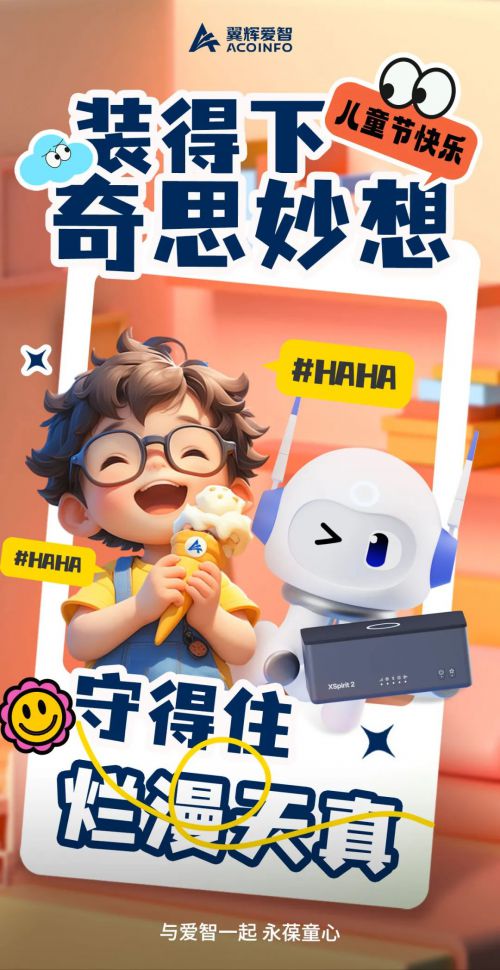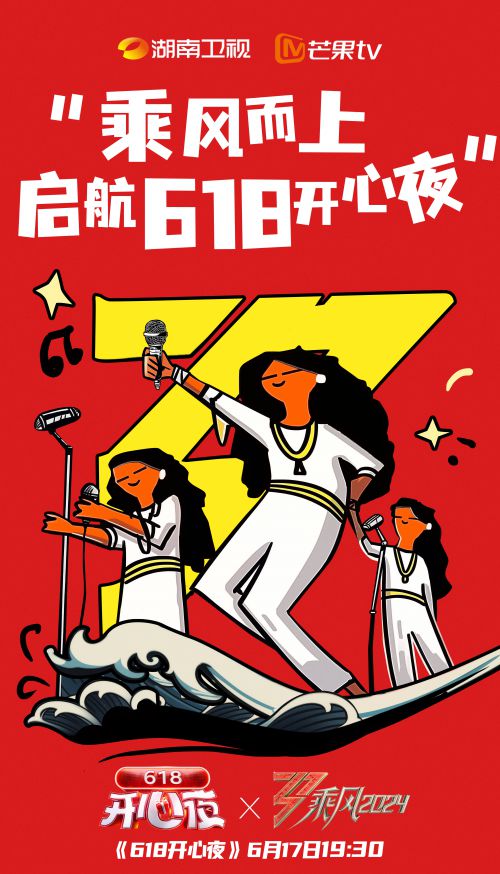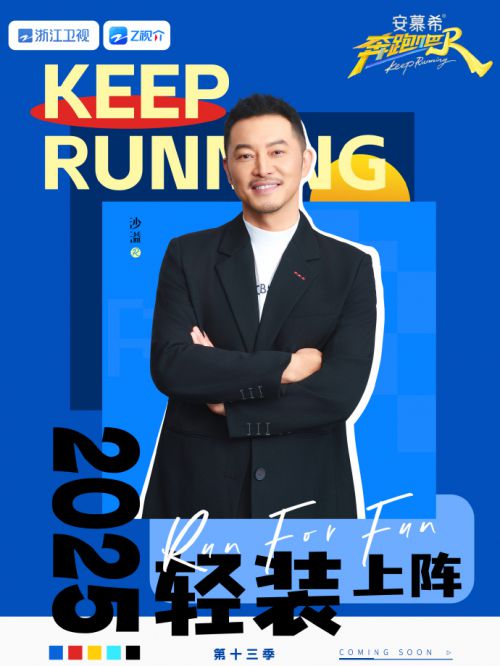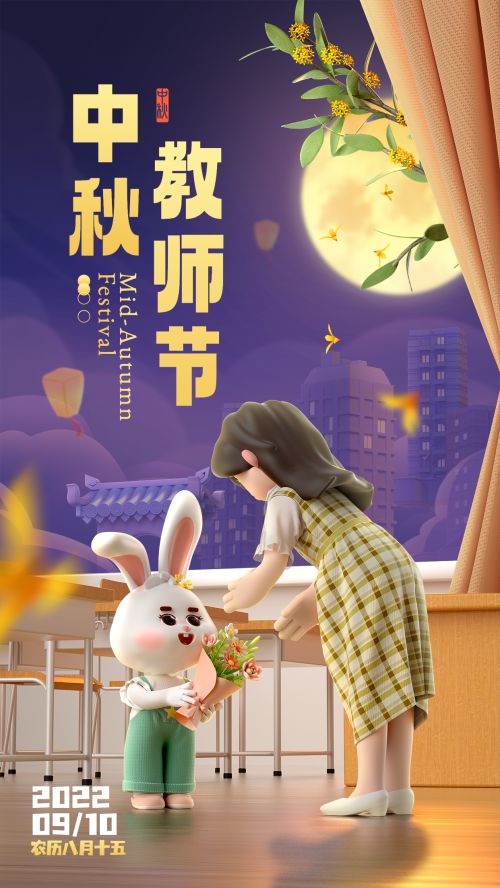
优设字由棒棒体
优设字由棒棒体是字由推出的一款创意卡通字体,以“棒棒”为设计灵感,传递轻松可爱的视觉感受,支持免费商用,适用于多元创意场景。 优设字由棒棒体字形方正稳重,重心居中带来平衡感,中宫宽博的设计让字符舒展透气,避免拥挤。笔画以“棍子”为原型,采用粗且均匀的线条,搭配方头笔型与斜切设计元素,兼具力量感与灵动性——粗线条如坚实的棒身,斜切处理则为笔画注入俏皮棱角,方头笔型更添利落质感。 优设字由棒棒体的笔画连接方式独特,采用断开设计打破传统字体的连贯感,如同孩童用彩棒拼搭的文字,天真烂漫;整体造型呼应“工作棒棒、身体棒棒”的美好寓意,让文字不仅是信息载体,更是情感传递的媒介。 无论是海报标题、电商Banner、儿童读物排版,还是短视频字幕、文创设计,优设字由棒棒体都能以鲜明的卡通风格点亮画面。免费商用的授权模式,更降低了创意成本,让设计师轻松实现趣味表达。